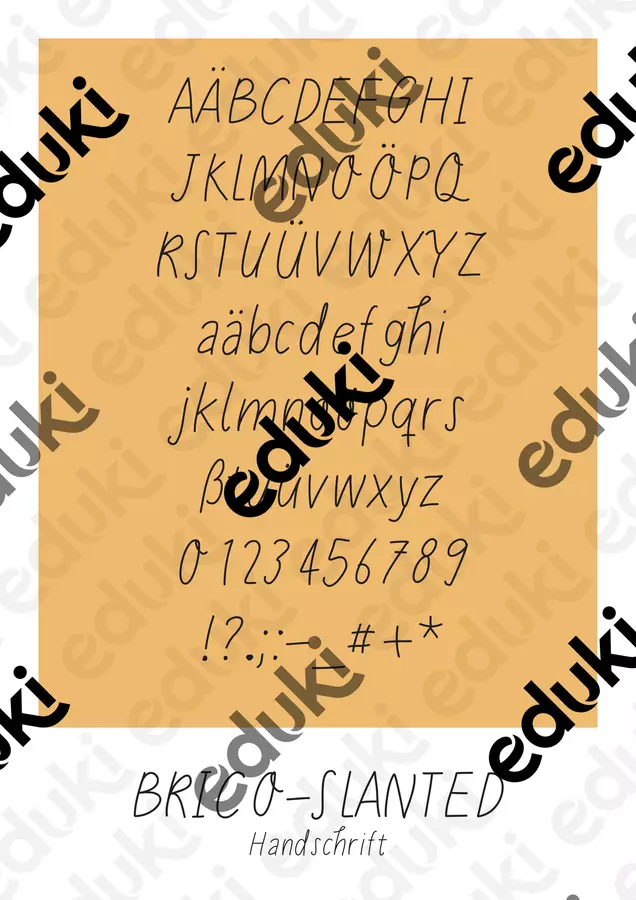
Selbsterstellte, kursive Handschrift, die sich wunderbar zur Erstellung von Arbeitsblättern oder anderem Unterrichtsmaterial eignet.
Schriftart für dein Arbeitsmaterial - Brico-Slanted